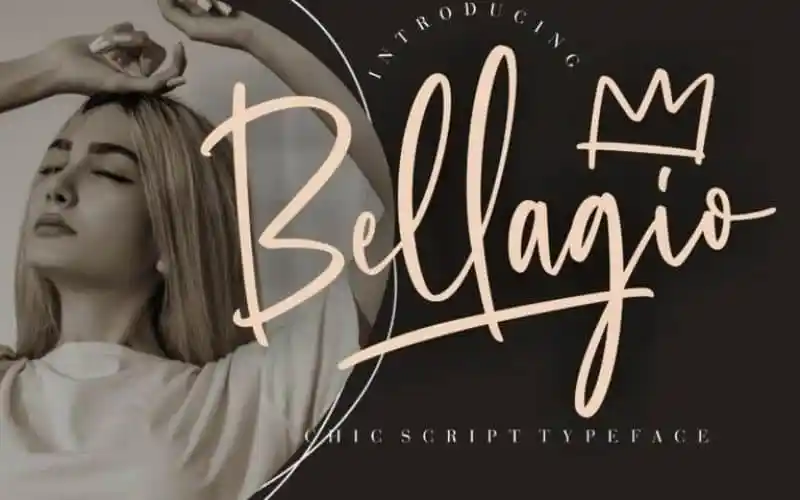
Bellagio Brush Font – Download Grátis
A Bellagio Brush Font é uma fonte à mão dourada com sabor, alegria e versatilidade, criada pelo Creatype Studio. Seu design elegante e delicado se destaca como a escolha perfeita para projetos de marca, logotipo, decorações de casamentos, posts nas redes sociais, anúncios, embalagens de produtos, designs dos produtos, etiquetas, fotografia, marcas de água, convites e estilização gráfica. Com sua suavidade e fidelidade a escrita à mão, Bellagio é perfeita para qualquer projeto que seja atraído pela essência do texto de letra, tornando-a uma opção ideal para qualquer aplicação visual que deseje adicionar um toque único e autêntico.